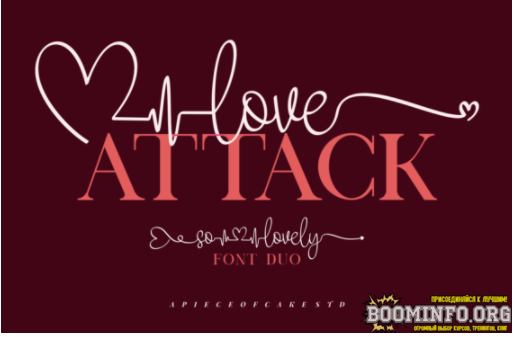
Creativefabrica Love Attack Font 2021
[Creativefabrica] Love Attack Font (2021)
Love Attack - это стильный и нежный рукописный дуэтный шрифт, подходящий для широкого спектра применений.
От поздравительных открыток до заголовков - вы можете добавить этот эффектный шрифт в любой из своих творческих проектов, и он гарантированно придаст им романтический рукописный оттенок.